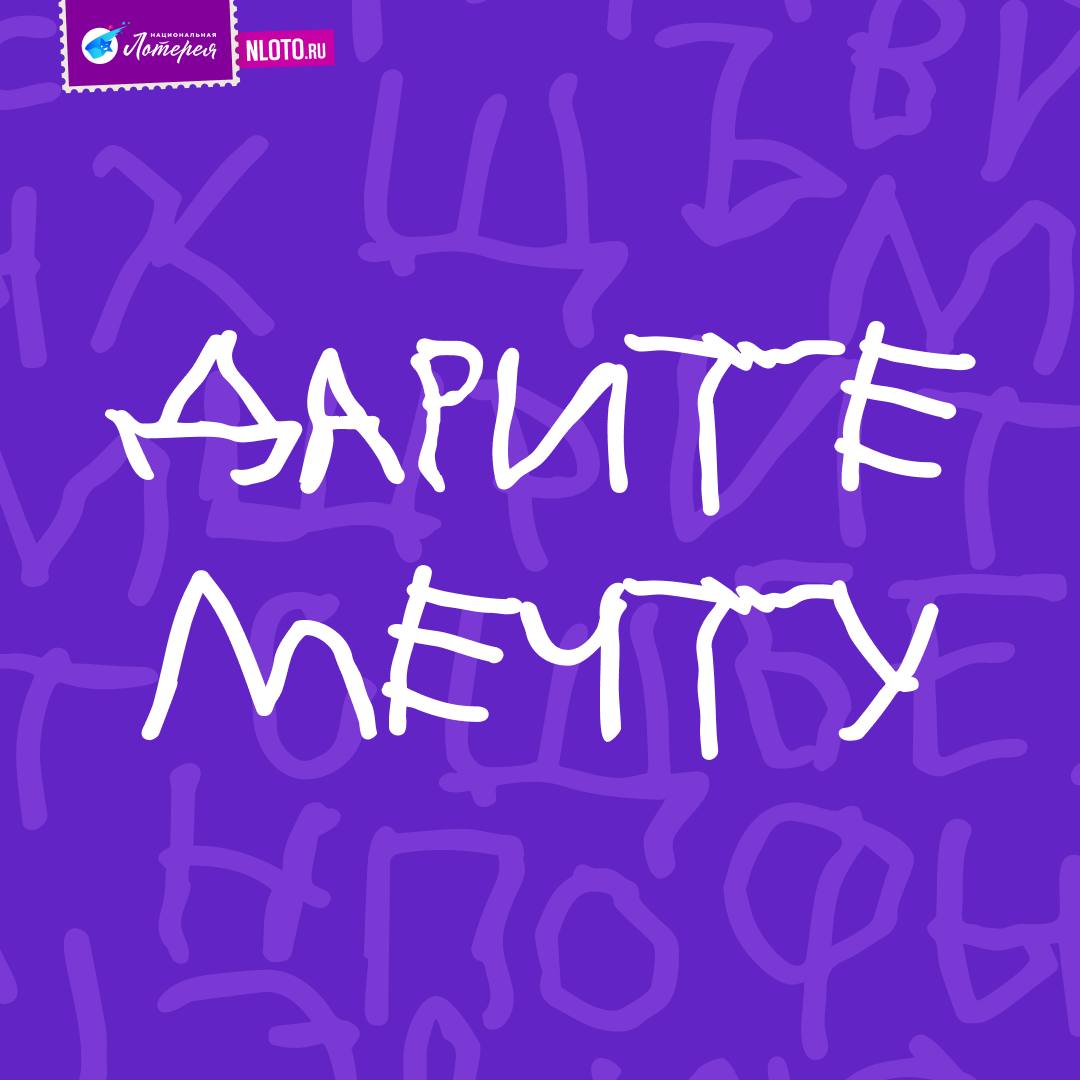
В знак поддержки и солидарности Международному дню ДЦП «Национальная Лотерея» поддержала проект Доброшрифт и запустила инициативу для помощи детям с ДЦП – подопечным БФ «Подарок Ангелу».
Ольга Костякова, руководитель департамента маркетинга и связей с общественностью «Национальной Лотереи»:
Наша совместная инициатива с «Доброшрифтом» и фондом «Подарок ангелу» направлена не только на сбор средств, но и на привлечение внимания общества к потребностям детей с церебральным параличом. До конца осени участники лотереи «Мечталлион» получают шанс не только выиграть суперприз от 100 млн рублей, но и возможность оказать реальную помощь детям. Уникальный шрифт, созданный на основе прописей детей с ДЦП, сделает визуальную составляющую кампании живой и доброй, подчёркивая идею инклюзивности.
Мы благодарим компанию «Национальная Лотерея» за неравнодушие к теме инклюзии и помощи детям. Практика отчислений с продажи лотерейных билетов на благотворительные цели является одним из самых простых и значимых инструментов поддержки социальных инициатив во всем мире. Нативная интеграция неровных букв, написанных детским спастическим почерком, в развлекательные продукты – это возможность реализации нашей основной миссии – уважительного отношения к людям с ДЦП и комплексной помощи подопечным детям из малообеспеченных и малоимущих семей.